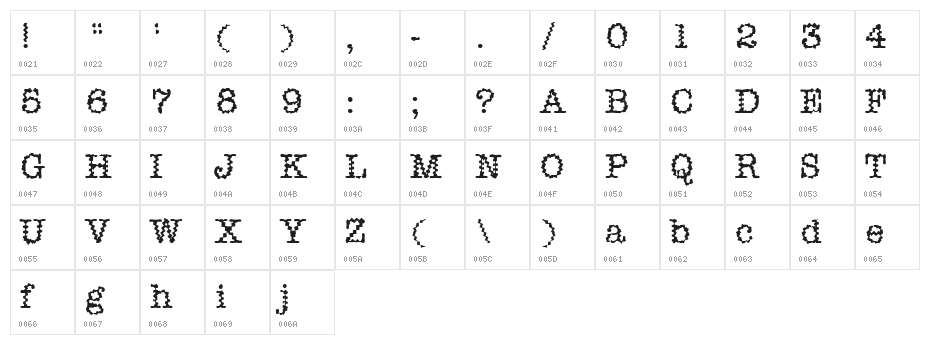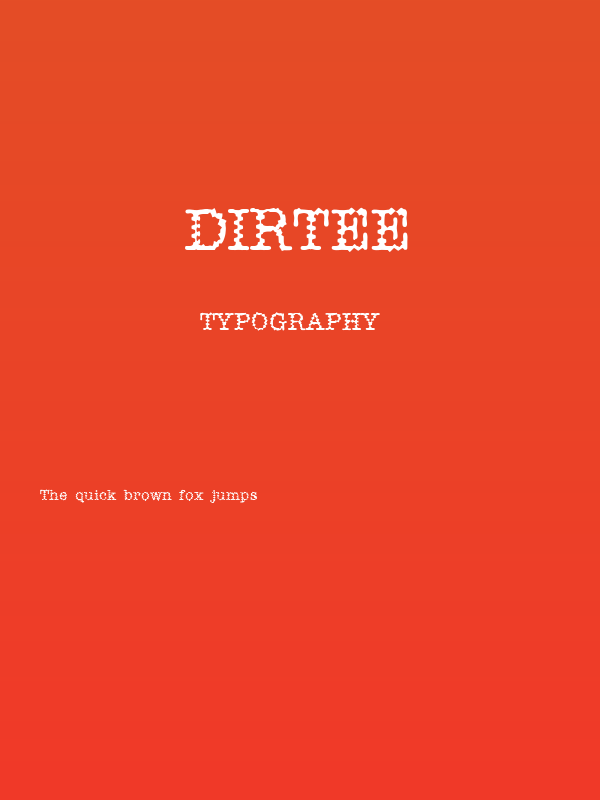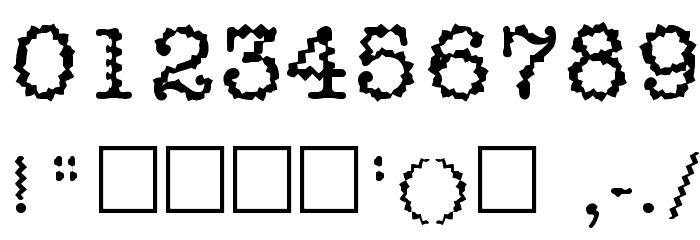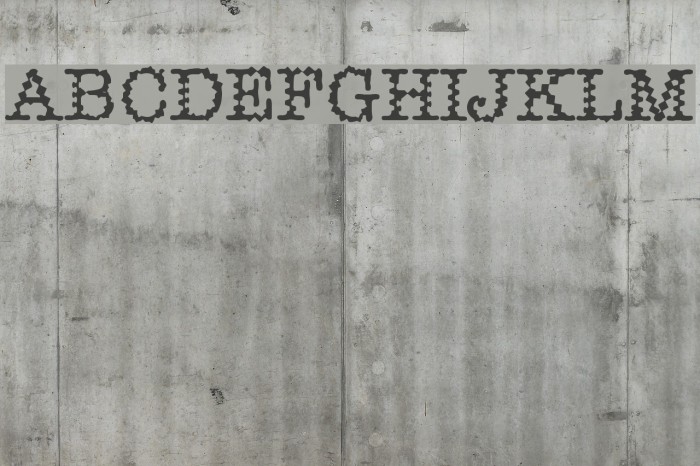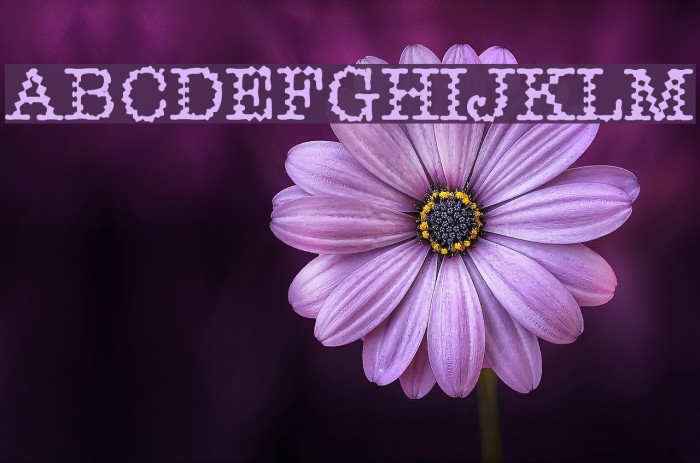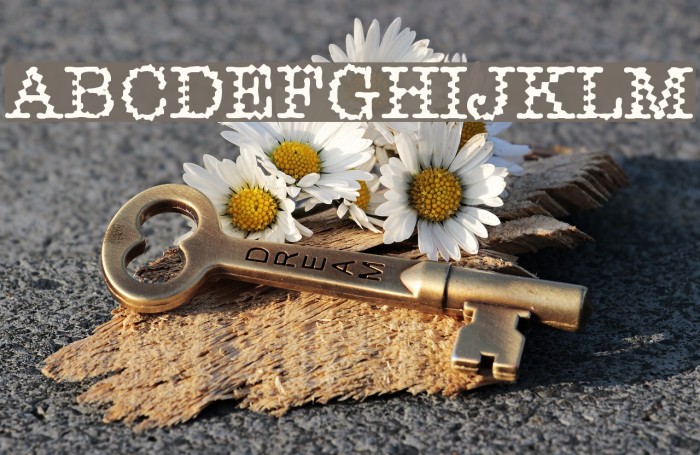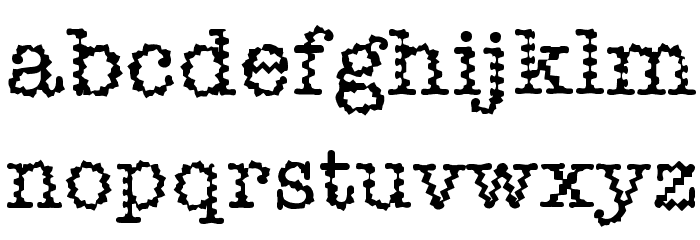
Dirtee Font
| Gesamtstil | Grunge, Urban, Edgy |
| Anwendungsfall | Headlines, Posters, Album covers |
| Vorgeschlagene Projekte | Ideal for album covers, posters, urban-themed designs, and any project needing a bold, edgy typeface. |